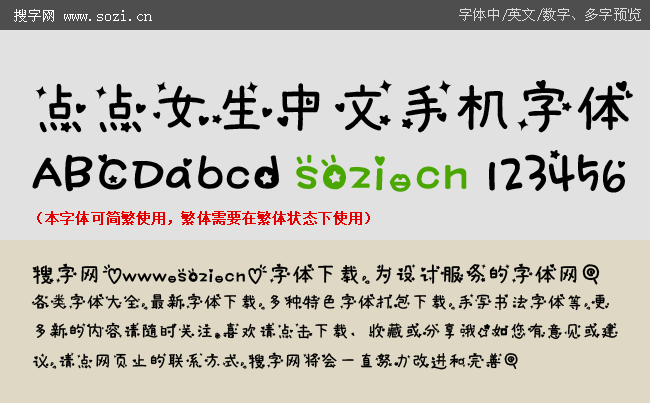
點(diǎn)點(diǎn)女生中文手機(jī)字體
搜字網(wǎng)給大家提供一款卡通手寫(xiě)風(fēng)格的手機(jī)中文字體下載。名字叫點(diǎn)點(diǎn)女生中文手機(jī)字體,這款手機(jī)字體是仿照兒童手寫(xiě)風(fēng)格的卡通手寫(xiě)字體,結(jié)構(gòu)帶有POP字體風(fēng)格,字體間還插入了卡通星星與心形圖案,特別適合喜歡卡通的朋友在手機(jī)上安裝使用。